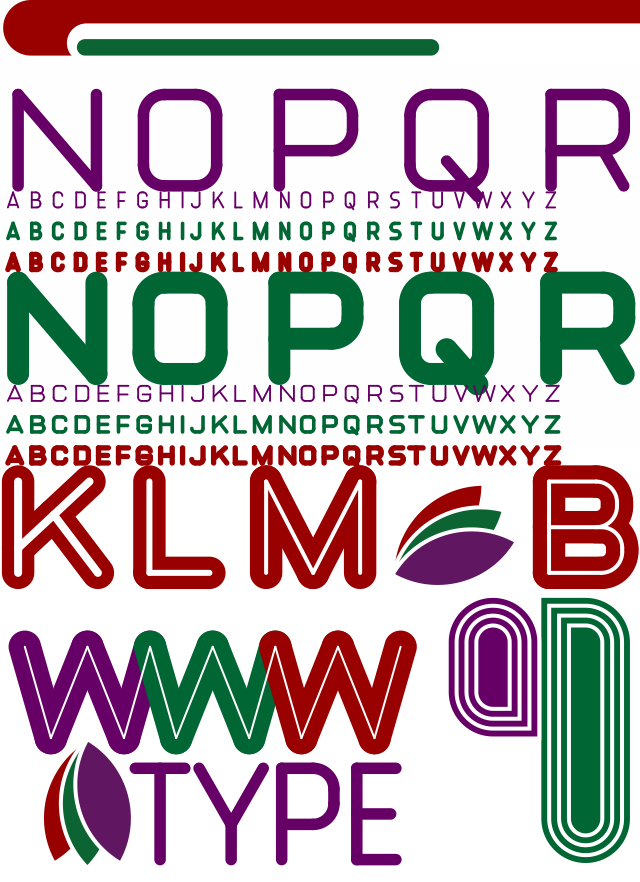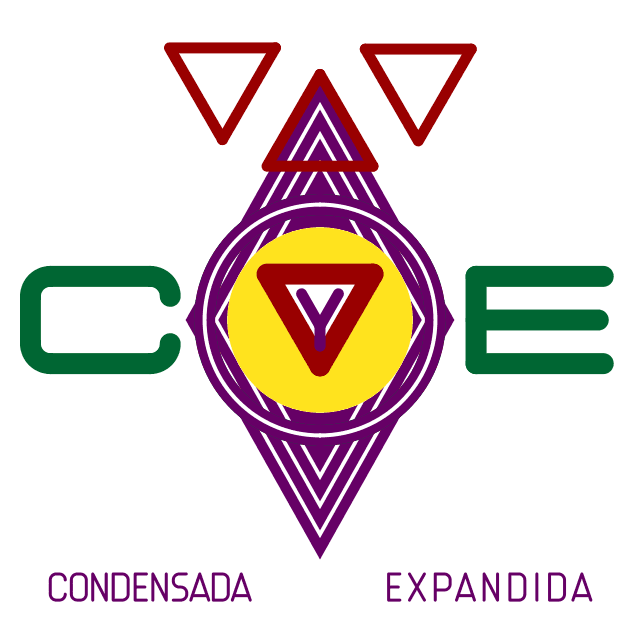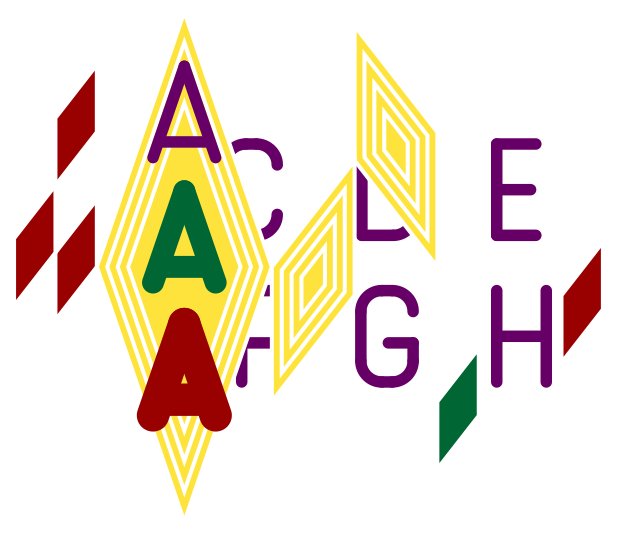
Tipografía C&E Rounded
Desarrollo de una tipografía para animación.
Los trazos no poseen modulación, por lo que sus trazos son siempre del mismo grosor en cada caracter.